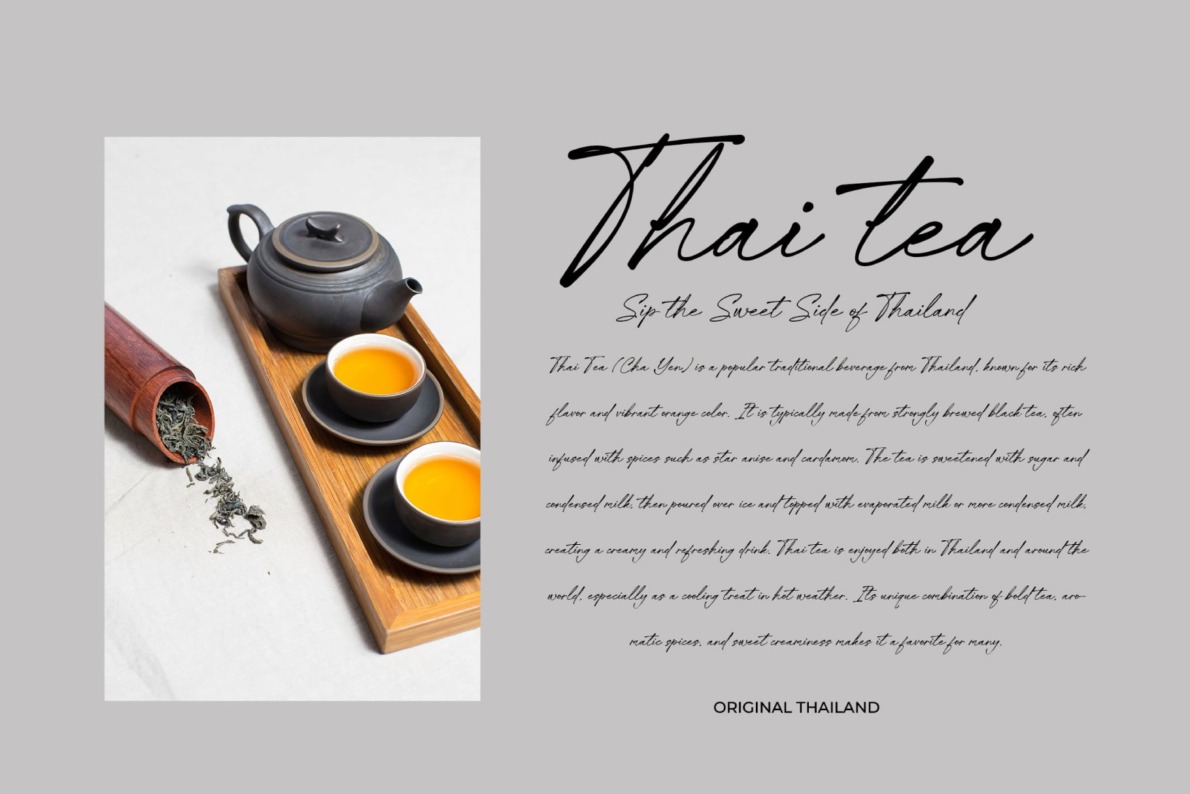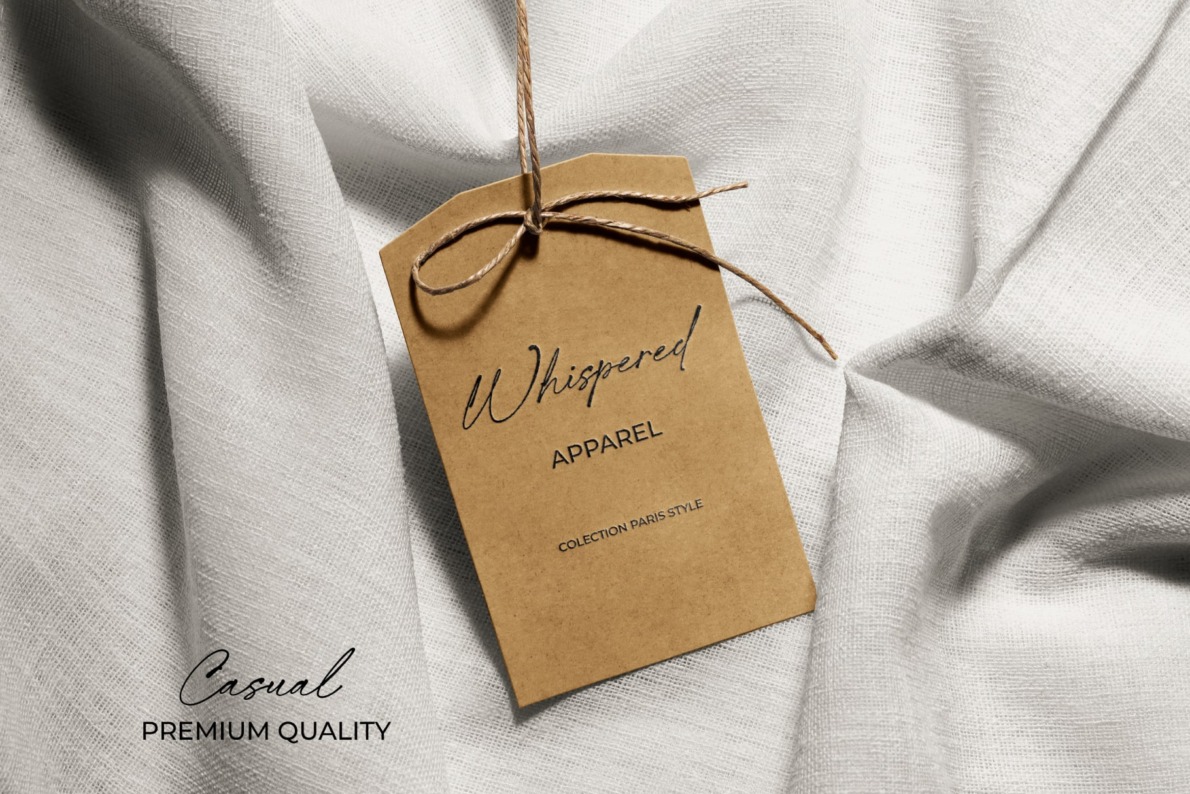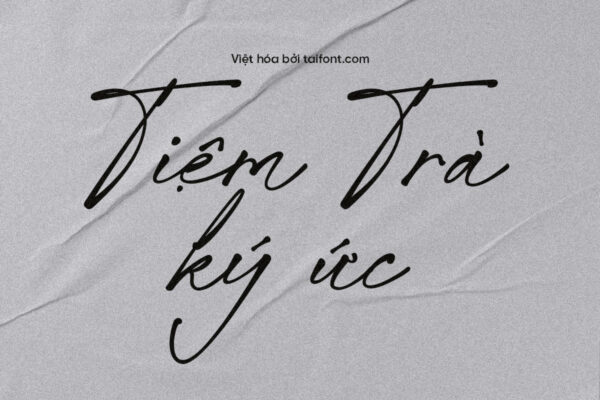
Giới thiệu Font TF Whispered Trails Việt hóa
TF Whispered Trails là một font viết tay thư pháp mang phong cách nét tự do, mang lại sự tinh tế, sang trọng và nghệ thuật cho bất kỳ thiết kế nào. Các đường nét mềm mại, nhẹ nhàng và tự nhiên giúp font này trở thành lựa chọn lý tưởng cho các dự án thiết kế đòi hỏi sự sáng tạo và cá nhân hóa cao.
Phiên bản Việt hóa của TF Whispered Trails hỗ trợ đầy đủ dấu tiếng Việt, giúp font dễ dàng ứng dụng vào nhiều mục đích khác nhau. Đây là sự lựa chọn hoàn hảo cho các thiết kế thiệp cưới, thiệp mời sự kiện sang trọng, bao bì thời trang, tạp chí cao cấp hoặc các sản phẩm sáng tạo khác.
Nếu bạn đang tìm kiếm một font Việt hóa miễn phí mang phong cách thư pháp, với các nét tự do và mềm mại, TF Whispered Trails là sự lựa chọn hoàn hảo cho thiết kế của bạn.
Điểm nổi bật của TF Whispered Trails Việt hóa
Việt hóa đầy đủ dấu tiếng Việt.
Kiểu chữ thư pháp với các nét tự do, nhẹ nhàng và tinh tế.
Lý tưởng cho thiệp cưới, thiệp mời, bao bì thời trang và các thiết kế sáng tạo khác.
Tạo cảm giác nghệ thuật, sang trọng và cá nhân hóa
Font TF Whispered Trails Việt Hóa – Font Viết Tay Thư Pháp Cho Thiết Kế Thiệp Và Thời Trang